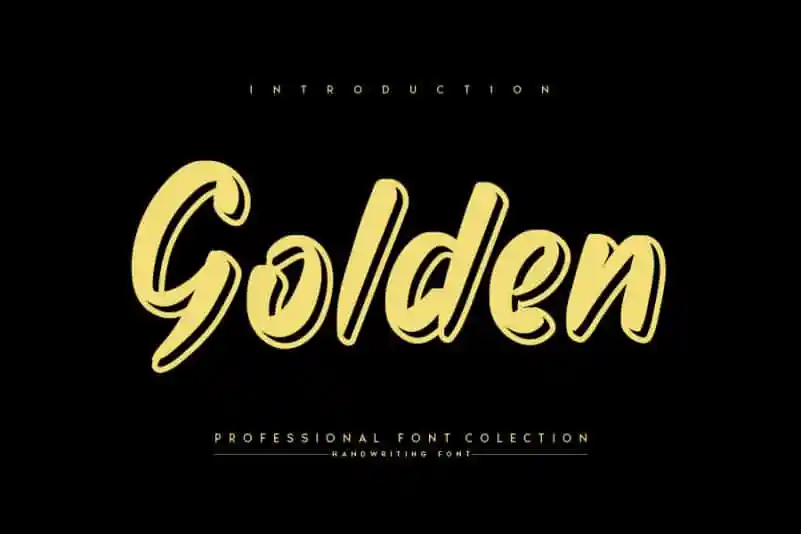
Golden Display Font – Download Grátis
A Golden Display Font é uma fonte de exibição fluida e encantadora, perfeita para aqueles que procuram algo elegante e versátil para suas criações criativas. Com seu design fluido e belo, esta fonte adicionada a seus projetos pode dar vida aos ideias originais e inovadoras. Seja você um designer gráfico experiente ou iniciante, a Golden Display Font está aqui para tornar seus trabalhos ainda mais memoráveis e imprimíveis. Idealmente recomendada como uma fonte escrita à mão, esta elegante fonte traz vida ao texto, dando-lhe um toque sofisticado que certamente fará sua obra de arte destacar. O designer Andikastudio criou esta font com cuidado para oferecer não apenas beleza visual, mas também funcionalidade, garantindo que a Golden Display Font seja uma escolha conveniente e de qualidade para qualquer projeto de design.